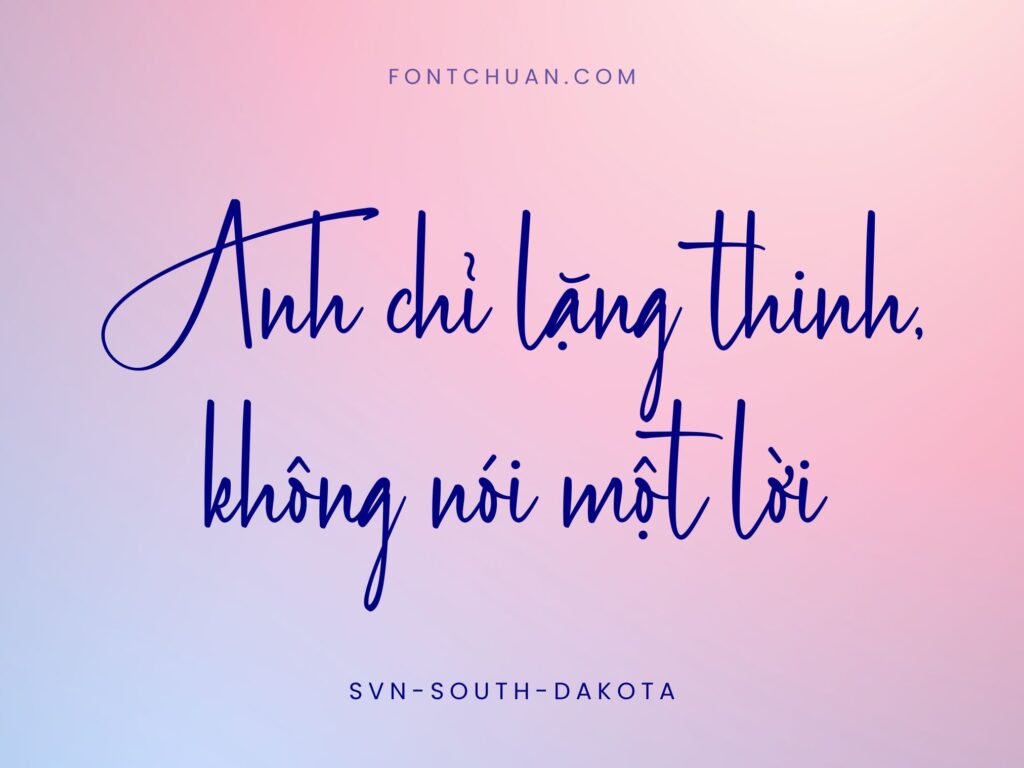
Font SVN South Dakota Việt Hóa
Tác giả Font: Widiyanti & Sarah Suci P
Font SVN South Dakota là phiên bản Việt hóa của kiểu chữ South Dakota, được thực hiện bởi STYLEno.1 Fonts. South Dakota là một font chữ ký viết tay tinh tế, được thiết kế bởi Widiyanti & Sarah Suci P và phát hành bởi CalligraphyFonts.net. Font này nổi bật với các ký tự mềm mại, thanh thoát, mang đến vẻ đẹp hiện đại và sang trọng. South Dakota bao gồm đầy đủ các ký tự chữ hoa, chữ thường, chữ số và các ký tự đặc biệt, hỗ trợ đa ngôn ngữ, phù hợp cho nhiều mục đích sử dụng khác nhau như thiết kế logo, tiêu đề, bao bì sản phẩm và các ấn phẩm truyền thông.
SVN South Dakota lý tưởng cho các dự án thiết kế yêu cầu sự thanh lịch và chuyên nghiệp, như thiết kế logo, tiêu đề, bao bì sản phẩm và các ấn phẩm truyền thông. Các ngành nghề như thiệp cưới, giáo dục và bất động sản có thể tận dụng font này để tạo điểm nhấn trong thiết kế. Ngoài ra, font cũng thích hợp cho các sự kiện như Tết, Valentine, Sinh nhật và các lễ hội khác.